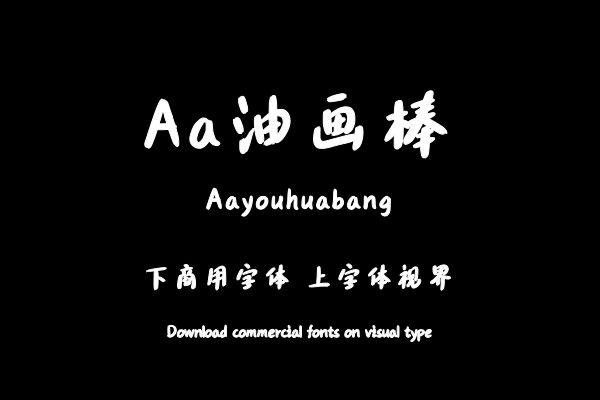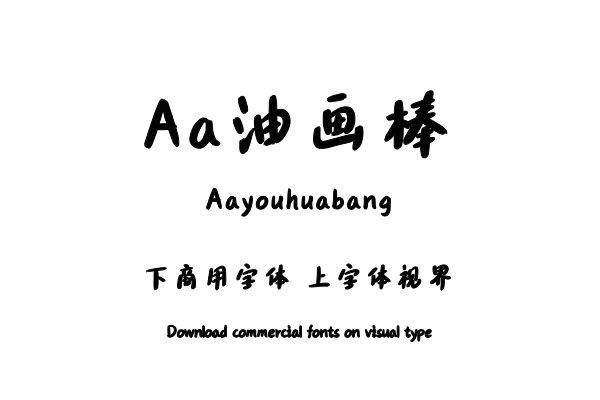
让手写形式成为字体设计的新领域,丰富创意标题字体风格。笔画圆钝稚拙,字形的倾斜构成一种统一的手写感,笔端的不规则形状更显轻松随意。购买须知:“下载服务费”与“字体VIP”所获得字体 仅用于个人非商用, 商用请联系付费授权。本字体为电脑用字,手机没有root权限不支持直接手机换字(手机如何root,请自行百度搜索教程)。购买前请先 了解清楚后再付款 ,字体为虚拟产品无法回收 一旦购买不支持退款。